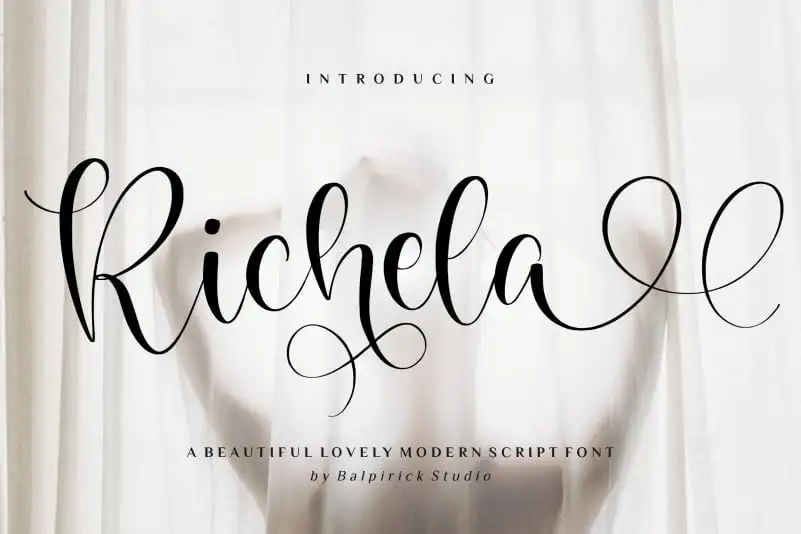
A fonte Richela Script é perfeitamente adequada para várias aplicações criativas em design, especialmente no campo da tipografia artística ou calligrafia digital. Suas linhas fluidas e detalhes elegantes tornam-a uma escolha única para criar designs de embalagem sofisticados para produtos, projetos de marca inovadores, revistas luxuosas ou até mesmo mensagens criativas para a internet social. Ainda mais impressionante, Richela Script também destaca-se em eventos memoráveis como casamentos e aniversários, onde seu estilo fluido complementa qualquer tipo de design do evento. Seja um slogan brilhante sobre a página inicial de uma revista ou simplesmente uma assinatura elegante para destacar texto importante acima de um fundo, Richela Script é um recurso indispensável para designers que buscam expressar a criatividade e o estilo em suas criações. Não importa qual aplicação você escolha, Richela Script atende perfeitamente as necessidades do seu projeto.